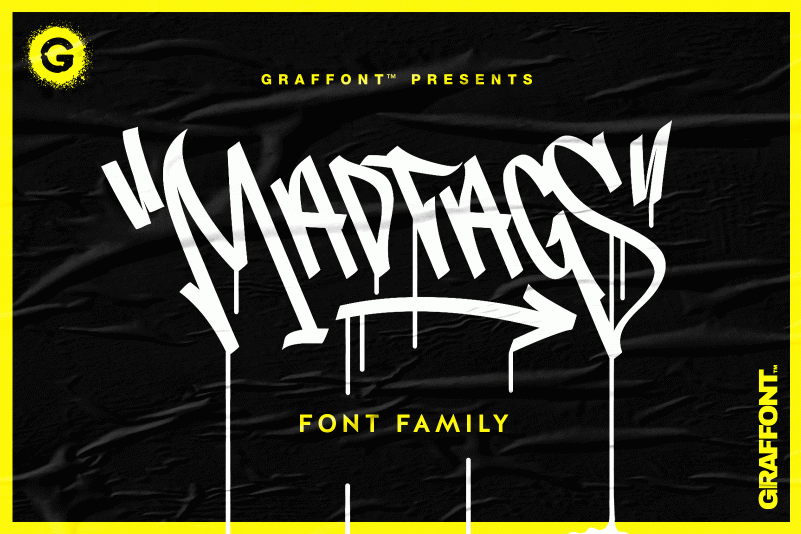
Madtags Font Family – Download Grátis
A Madtags Font Family é inspirada nos artefatos do graffiti urbano, principalmente nas marcas de artistas de rua feitas com tijolos chisoleados. Ela traz quatro estilos exclusivos e mais de 300 caracteres únicos para enriquecer seus trabalhos gráficos. Desenvolvida por Graffont, essa fonte do estilo graffiti é perfeita tanto para os desafios da arte em ruas quanto para o design digital. Seja você um designer ou um artista urbano, a Madtags oferece uma variedade de opções que vão enriquecer seus projetos digitais e físicos, tornando seu trabalho mais vibrante e inspirador.